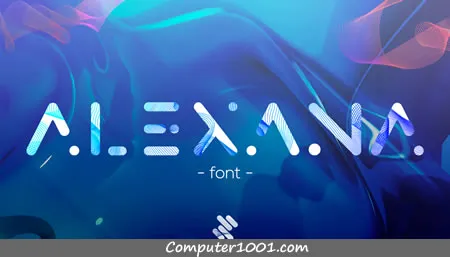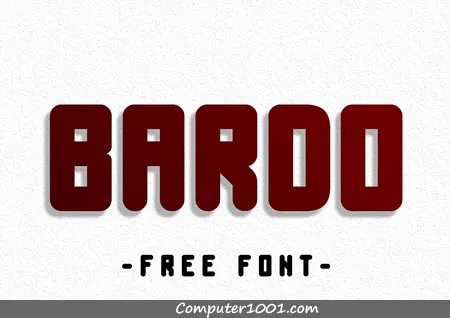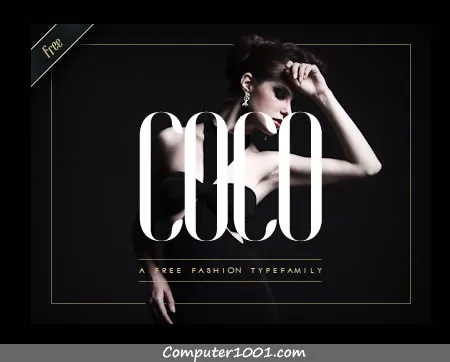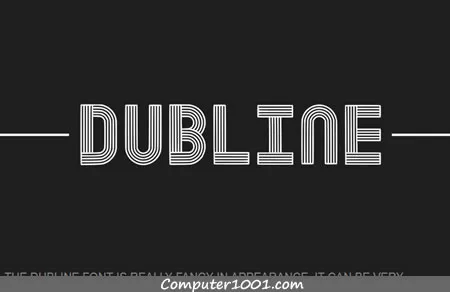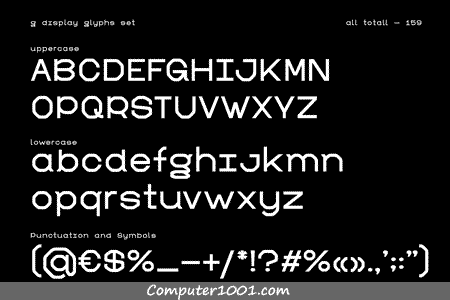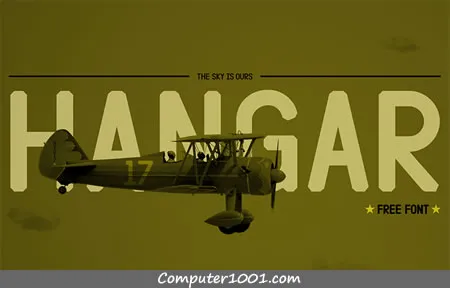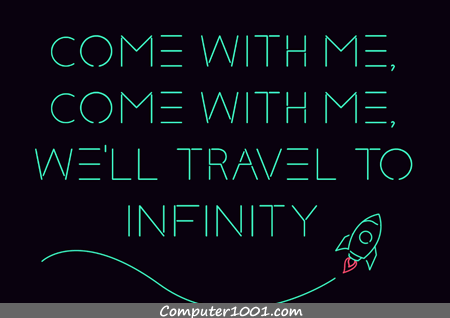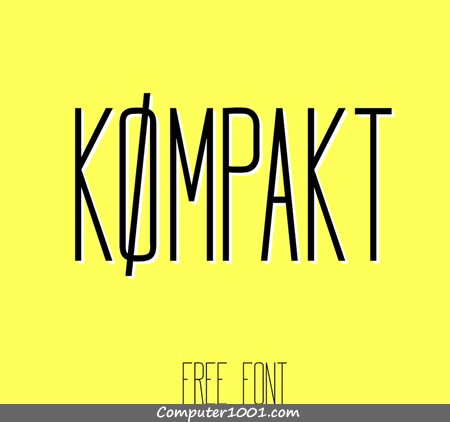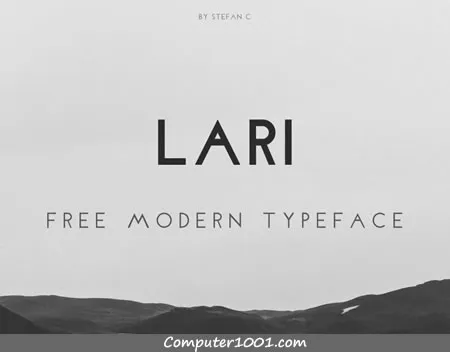
Kumpulan font yang keren ini cocok untuk poster, kartu nama, logo, newsletter, cover, spanduk, kaos, dan headline atau judul pada slide PPT, header Youtube, Twitter, Facebook; dan desain grafis lainnya.
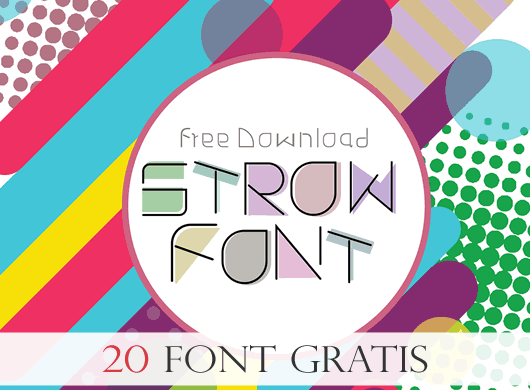
Pada masing-masing halaman font, Anda bisa melihat contoh penggunaan font pada berbagai desain dengan kombinasi warna dan background yang membuat tampilannya sangat atraktif dan indah. Contoh-contoh tersebut bisa Anda jadikan sebagai inspirasi dalam mendesain proyek Anda.
- Alexana
- Bardo
- Coco
- Dubline
- G Display
- Hangar
- Klaxons
- Kømpakt
- Lari
- Linircle
- Massa
- Megapolis Black
- Rana
- Rentukka
- RounD
- Skywalker
- Strow Font
- Tecnico
- Union Condensed
Font display yang berukuran besar dan menonjol sangat bagus untuk desain poster, selebaran, dan headline.